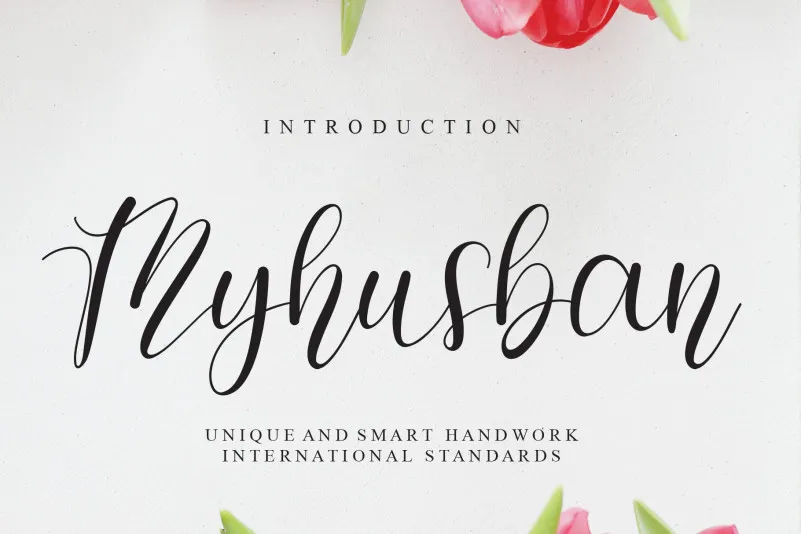
Myhusban Font – Download Grátis
Esta é uma fonte escrita à mão com traços círconflexuais que parece naturalmente atraente e elegante. Ela contém letras bem formadas e um estilo clean, garantindo que seus trabalhos fiquem ainda mais belos. Myhusban é perfeito para quem deseja adicionar uma pitada de personalidade aos textos, destacando-se em qualquer obra. Seja ela utilizada em logotipos, rótulos ou design editorial, a elegância e sofisticação desta fonte são certamente um convite à beleza.